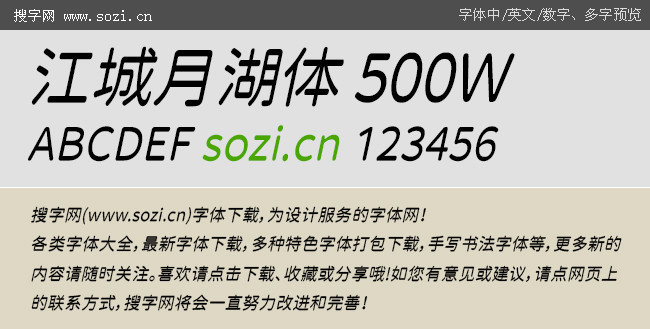
江城月湖體 500W
搜字網(wǎng)提供一款江城月湖體 500W中文藝術(shù)字體下載,江城月湖體是基于思源系列字體改造而成,所以擁有思源字體的超大字符集血統(tǒng),簡(jiǎn)體和繁體都基本上不缺字。這款字體字形靈秀清美,橫粗豎細(xì)的風(fēng)格頗為特別,圓潤(rùn)的筆畫中又帶著一點(diǎn)動(dòng)感,比較適合用作正文,標(biāo)題,偏柔美風(fēng)格的設(shè)計(jì)。